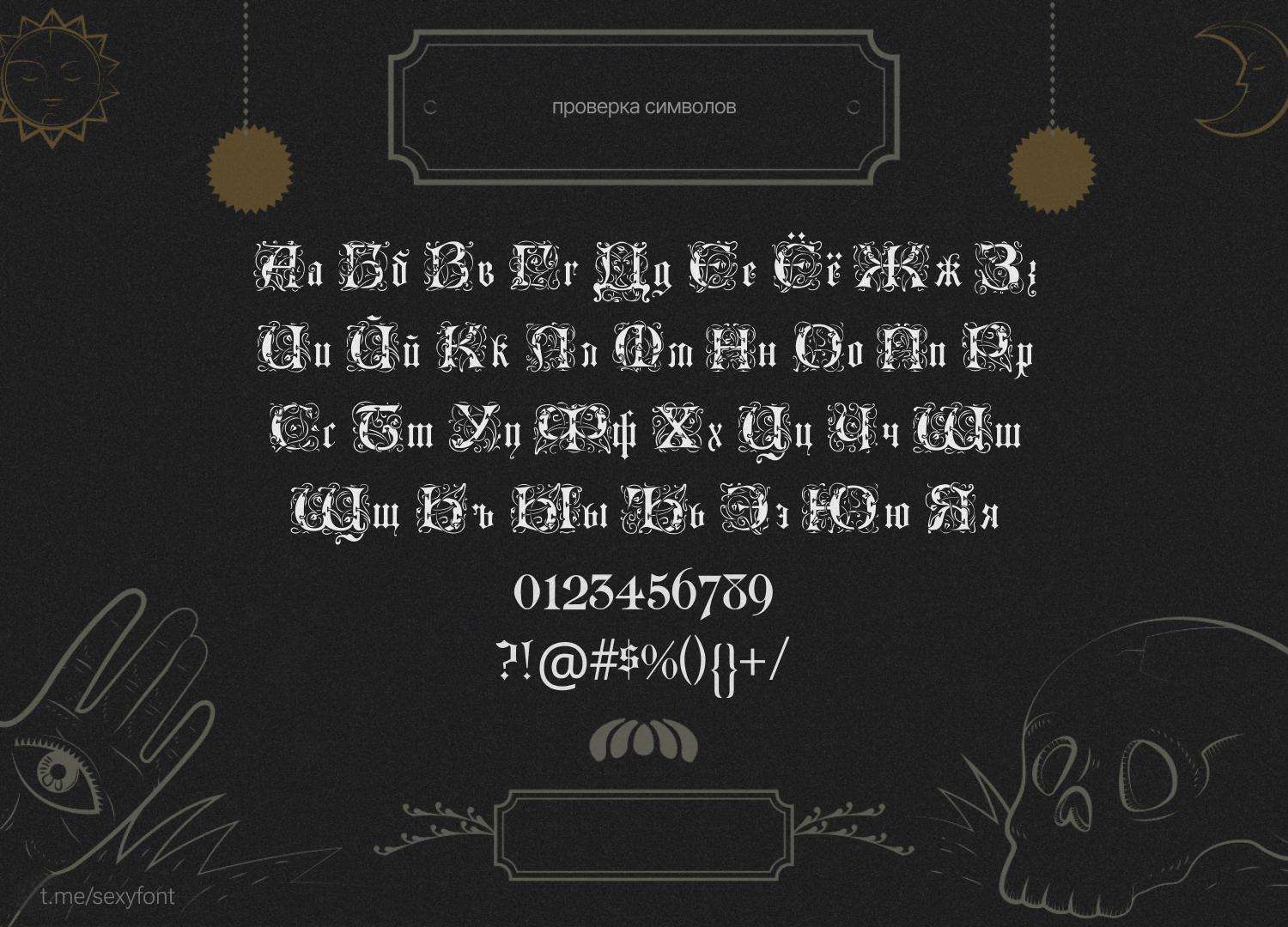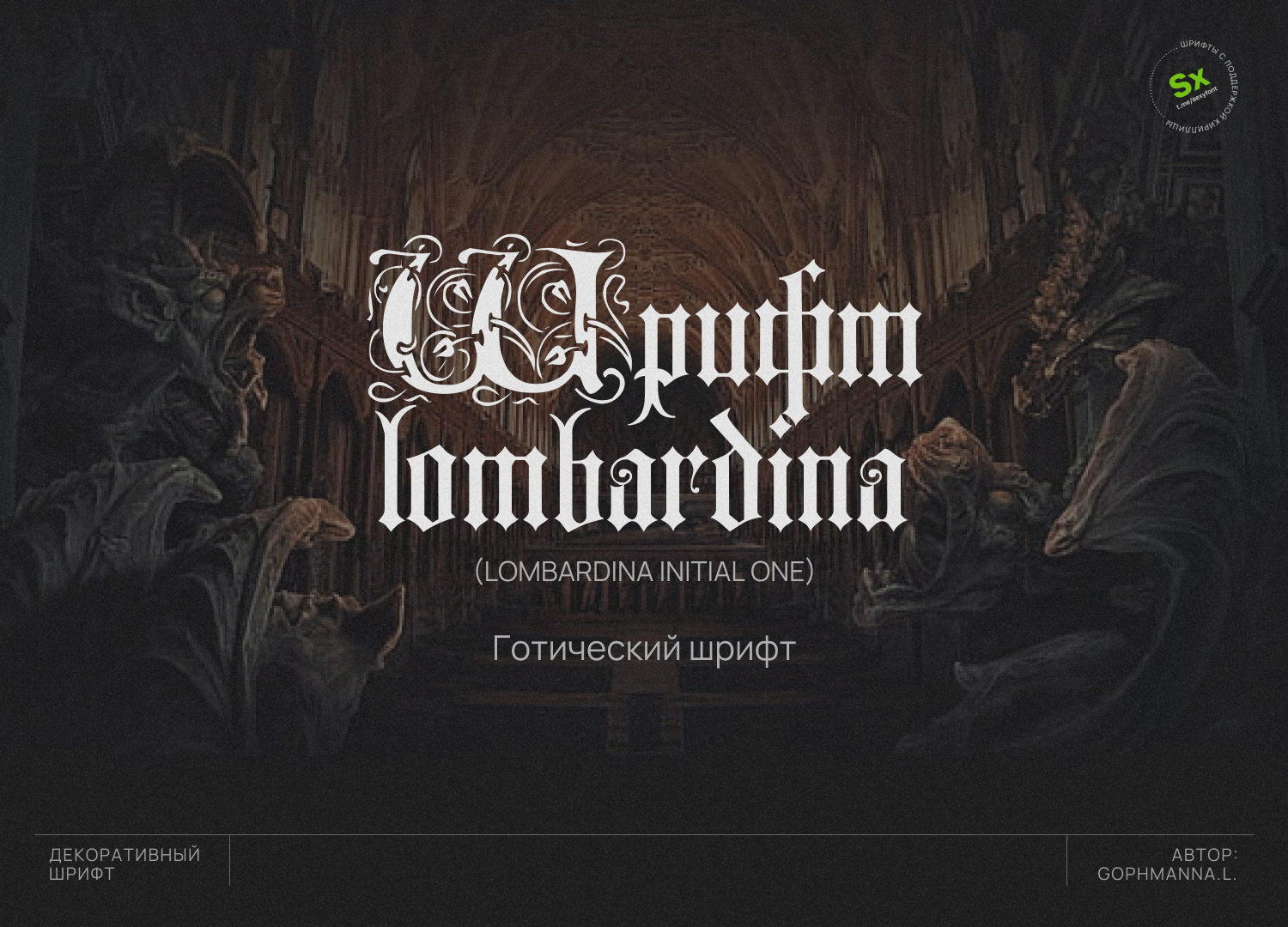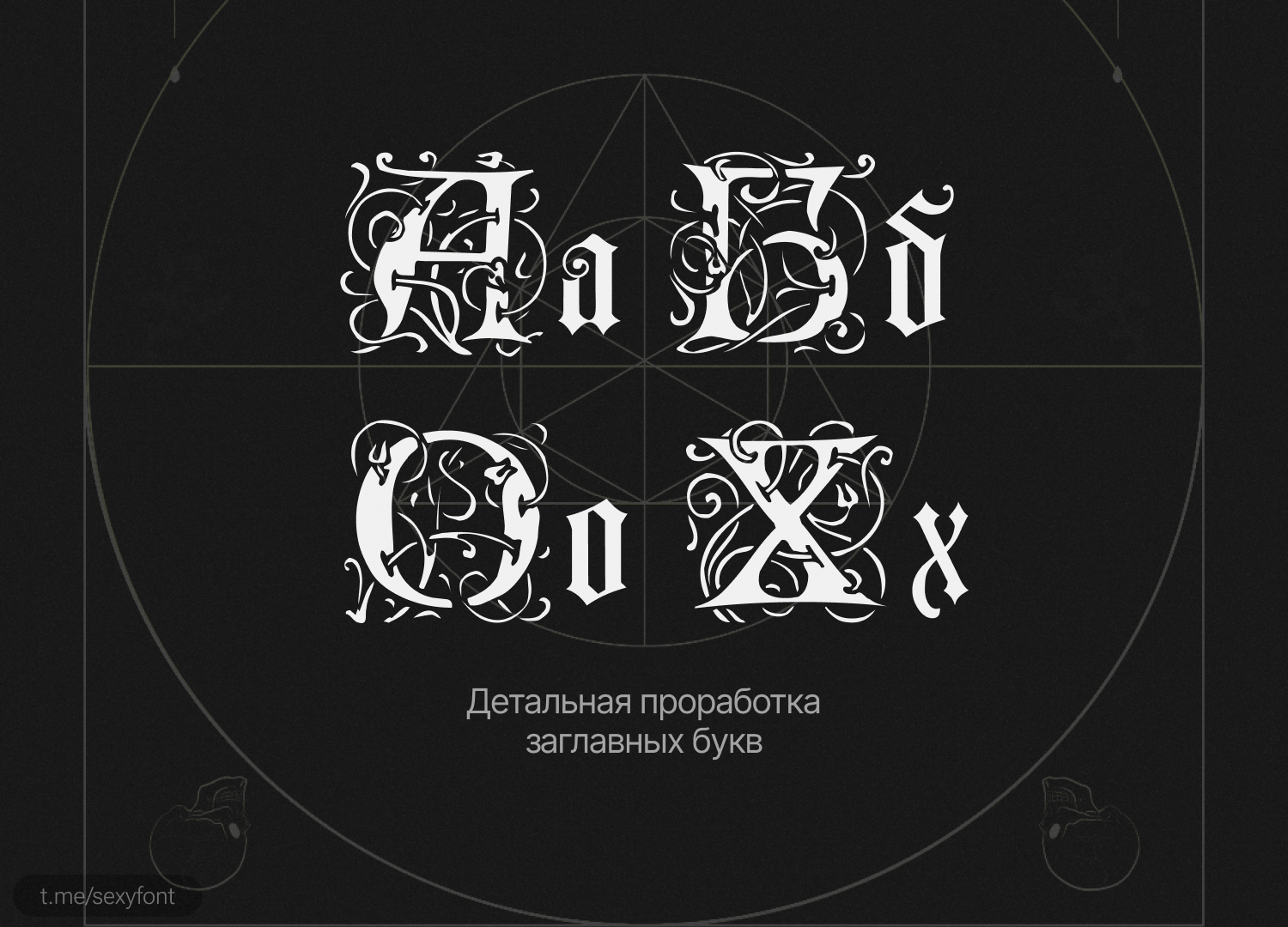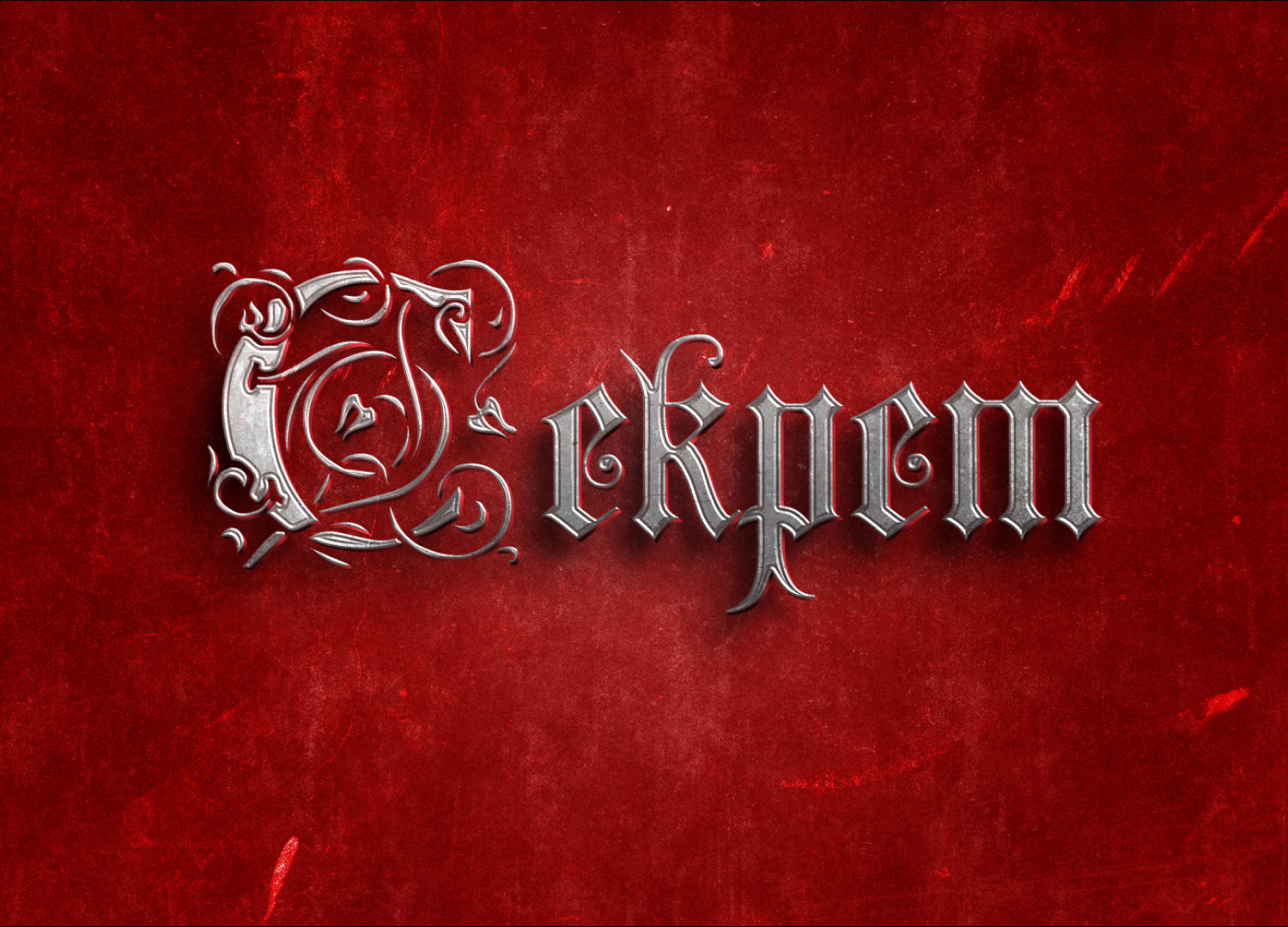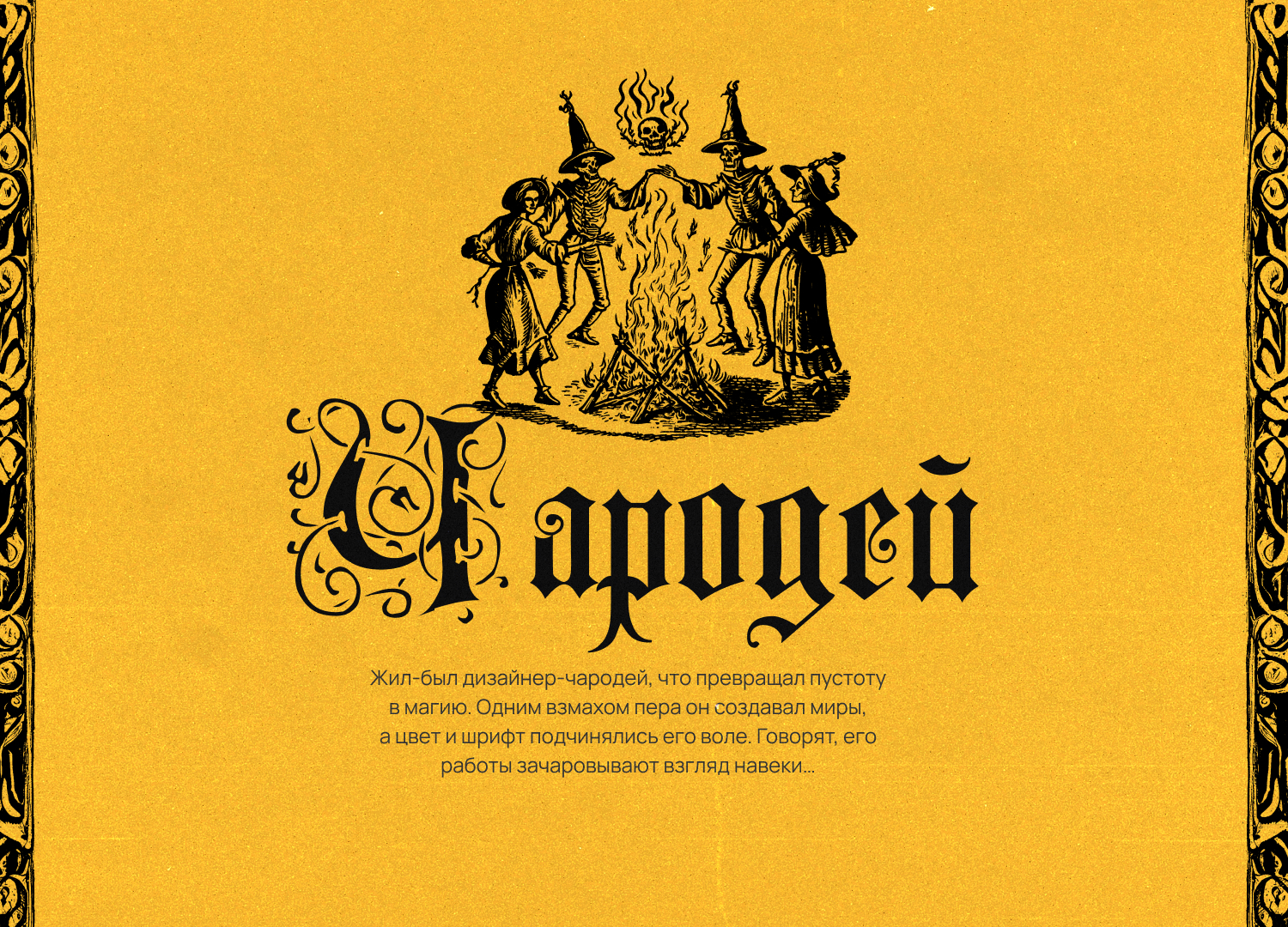
Готический шрифт с кириллицей
Сегодня делал презентацию на мистическую тему для нашего канала с исходниками. Использовал там готический шрифт Deutsch Gothic. Мне стало интересно, что еще есть на эту тему. И нашел lombardina initial
Забираем готический шрифтец. Да, читаемость не айс, но зато как эффектно сделаны заглавные буквы!)